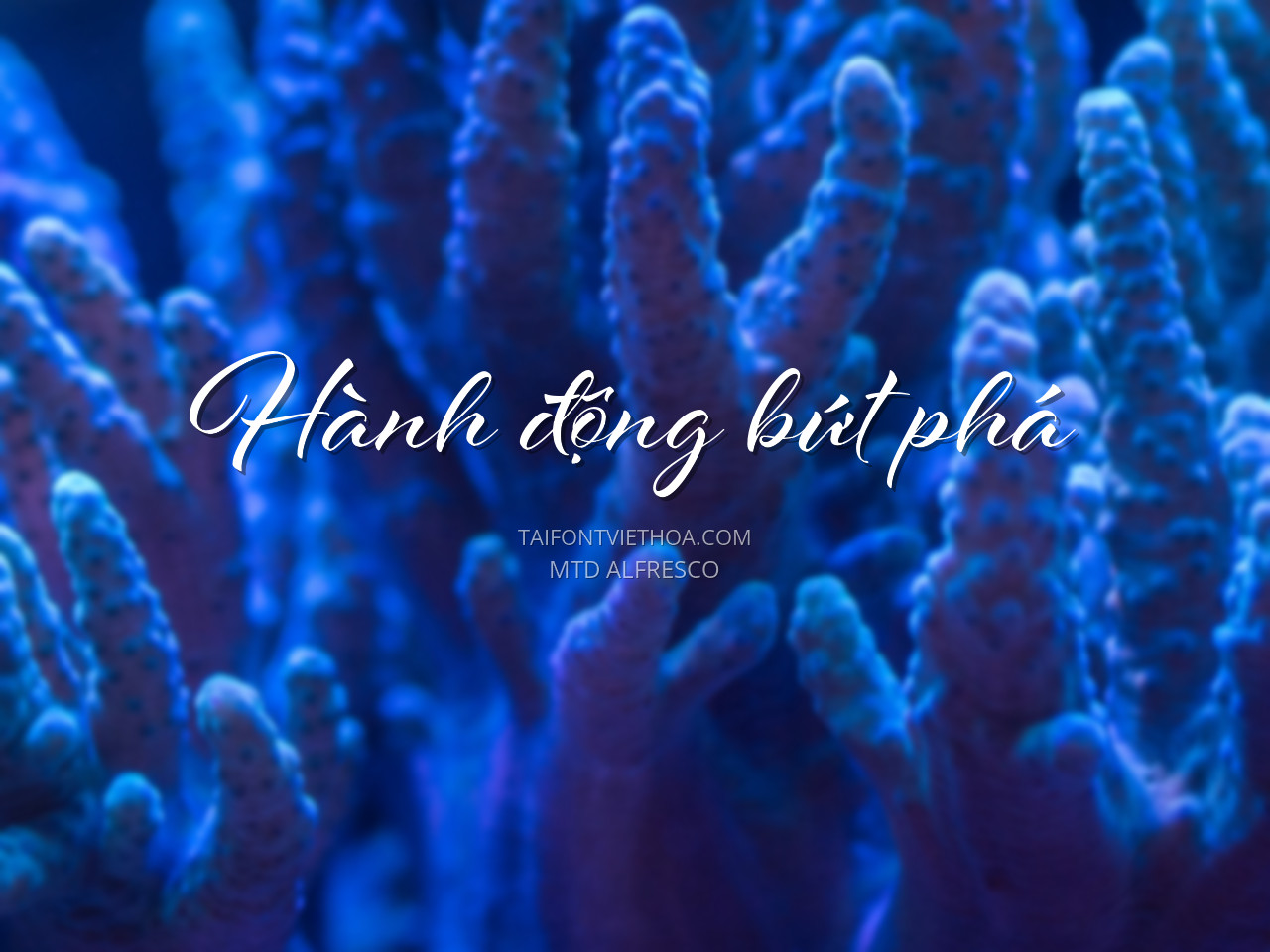
Giới thiệu về font Aifresco – Vẻ đẹp handwritten mềm mại và hiện đại đầy cảm xúc
Aifresco là một font viết tay hiện đại (handwritten script) được thiết kế với các đường nét nhẹ nhàng, uyển chuyển như những nét bút vẽ tự nhiên. Font mang đến cảm giác ấm áp, gần gũi nhưng không kém phần tinh tế, rất phù hợp cho các thiết kế mang tính cá nhân hoặc thương hiệu nhẹ nhàng. Tên gọi Aifresco gợi lên một không khí tươi mới, tự do, như được viết dưới ánh nắng sớm – đúng với tinh thần mềm mại và sáng tạo mà font truyền tải.
Phiên bản Việt hóa do Mộc Hạthực hiện đã tối ưu hoàn toàn cho tiếng Việt, giữ nguyên độ bay bổng và uyển chuyển của bản gốc. Taifontviethoa.comđã lựa chọn và chia sẻ font Aifresco như một công cụ hoàn hảo cho những nhà thiết kế cần một kiểu chữ viết tay nghệ thuật, giàu cảm xúc để truyền tải thông điệp nhẹ nhàng nhưng đầy ấn tượng.
Đặc điểm thiết kế bay bổng và ứng dụng lý tưởng của font Aifresco
Aifresco có form chữ nghiêng nhẹ, độ cong mềm, kết hợp ligatures mượt mà giữa các ký tự tạo cảm giác tự nhiên như viết tay. Nét chữ thanh mảnh, tinh tế, không quá cầu kỳ nhưng vẫn toát lên sự chăm chút trong từng chi tiết, tạo nên tổng thể trang nhã và nữ tính.
Font phù hợp để sử dụng trong: thiệp cưới, thiết kế blog cá nhân, logo thương hiệu handmade, bao bì mỹ phẩm tự nhiên, trích dẫn truyền cảm hứng hoặc bài đăng mạng xã hội mang tính storytelling. Ngành nghề lý tưởng: cưới hỏi, mỹ phẩm, thời trang nữ, thủ công mỹ nghệ, thiết kế sáng tạo, lifestyle và các thương hiệu hướng đến khách hàng nữ, trẻ và yêu thích cái đẹp nhẹ nhàng.